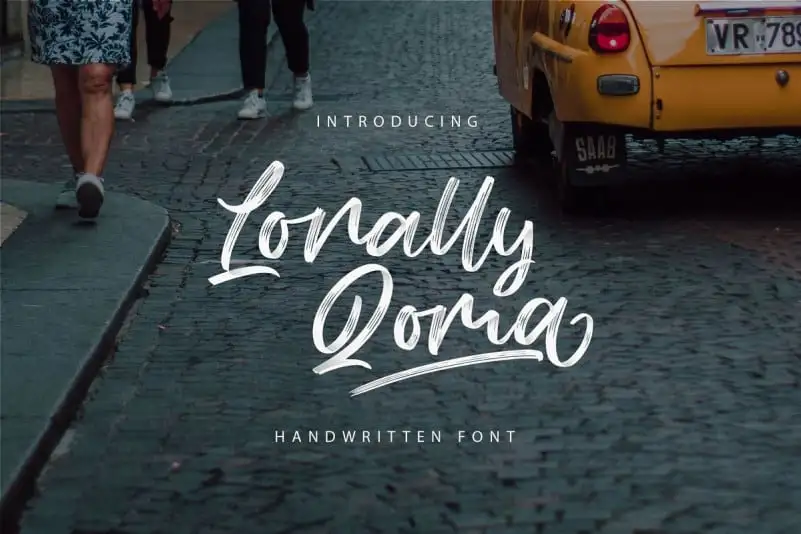
Lonally Qoma Brush Font – Download Grátis
A “Lonally Qoma Brush Font” é uma tipografia masculina em caixa alta com traços grossos em cada glyph, criada pelo font designer alit design. Esta elegante e única fonte vem com um deslumbrante sopro de ligatura que proporciona surpresas únicas em diferentes combinações de caracteres da mesma fonte. Ideal para várias aplicações como cartões de convite, embalagens de produtos, design web, cartazes digitais ou até mesmo a impressão de citações – esta font está perfeitamente adaptada para tornar o seu trabalho ainda mais impressionante e distintivo. Com certeza um excelente complemento para qualquer projeto gráfico moderno que busca expressar sofisticação e originalidade.